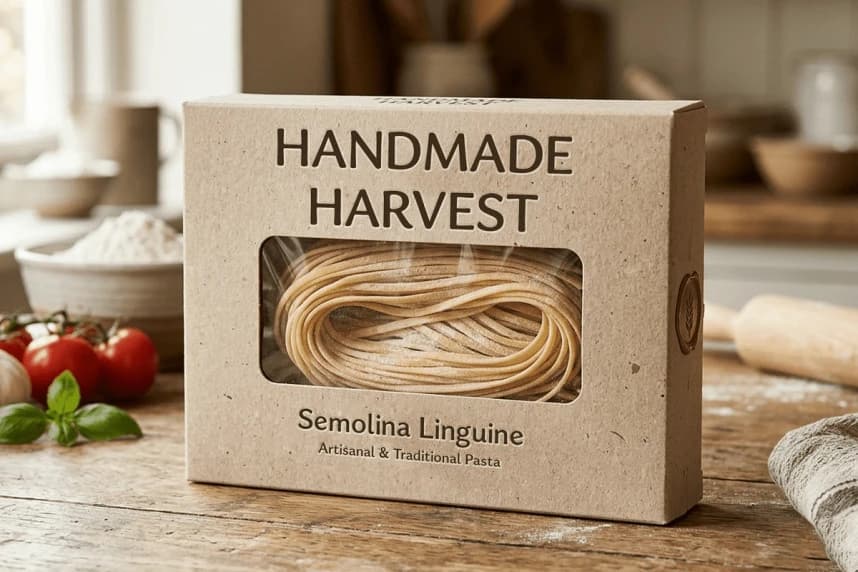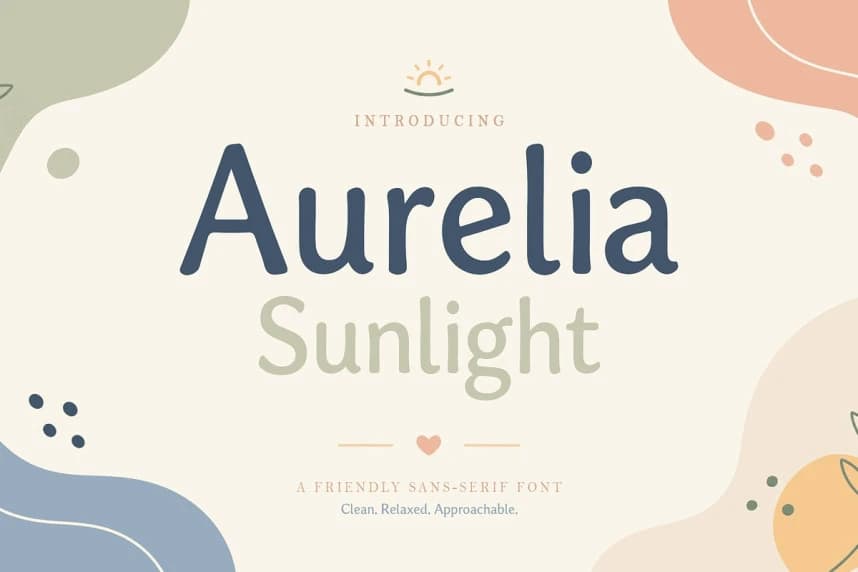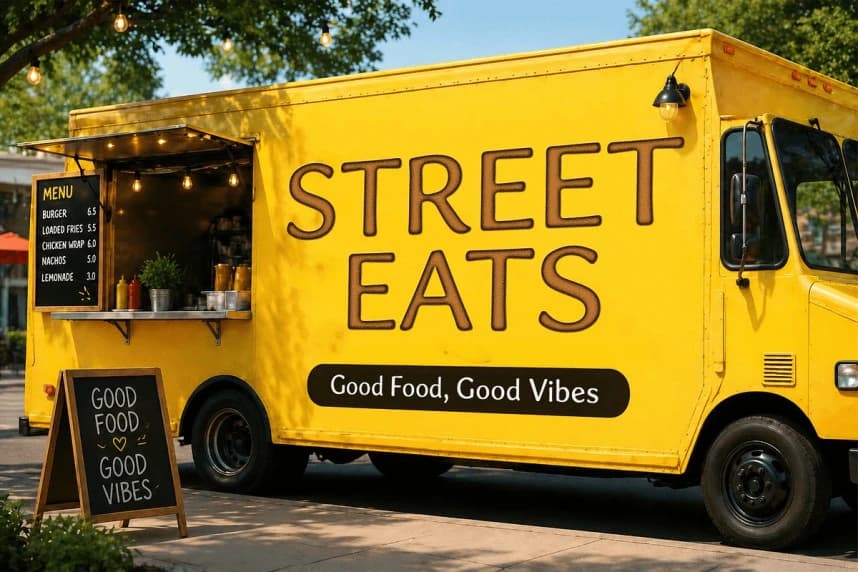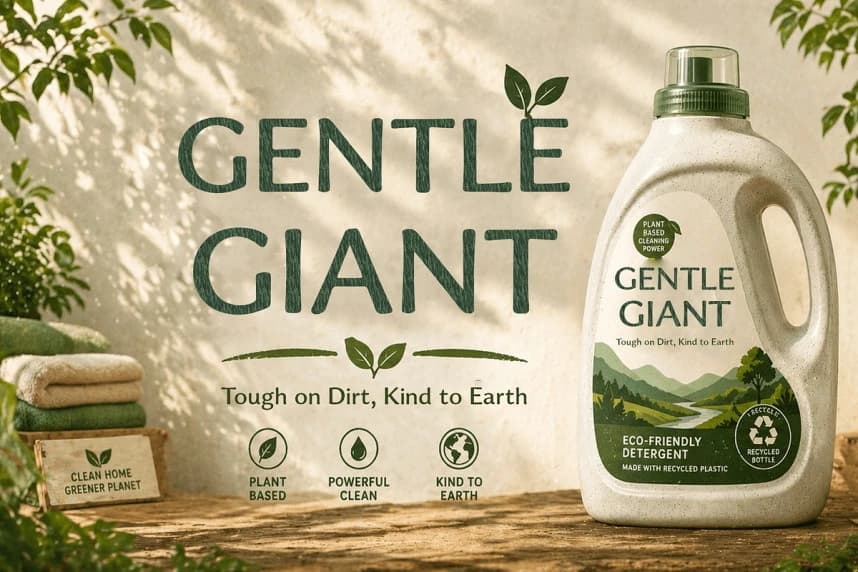
Aurelia Sunlight Font, sıcak ve hümanist bir display yazı tipidir; yumuşaklık ve karakteri yansıtır. Organik eğriler ve kendinden emin çizgilerle tasarlanan bu yazı tipi, herhangi bir tasarıma dostça ama zarif bir duruş kazandırır — markalaşma, editoryal başlıklar ve ambalaj için mükemmel.
Aurelia Sunlight Font, sıcak ve hümanist bir display fontudur; yumuşaklık ve karakter yayar. Organik eğriler ve kendinden emin çizgilerle tasarlanmıştır; her tasarıma dostça ama zarif bir hava katar — marka tasarımı, editoryal başlıklar ve ambalaj için mükemmel.